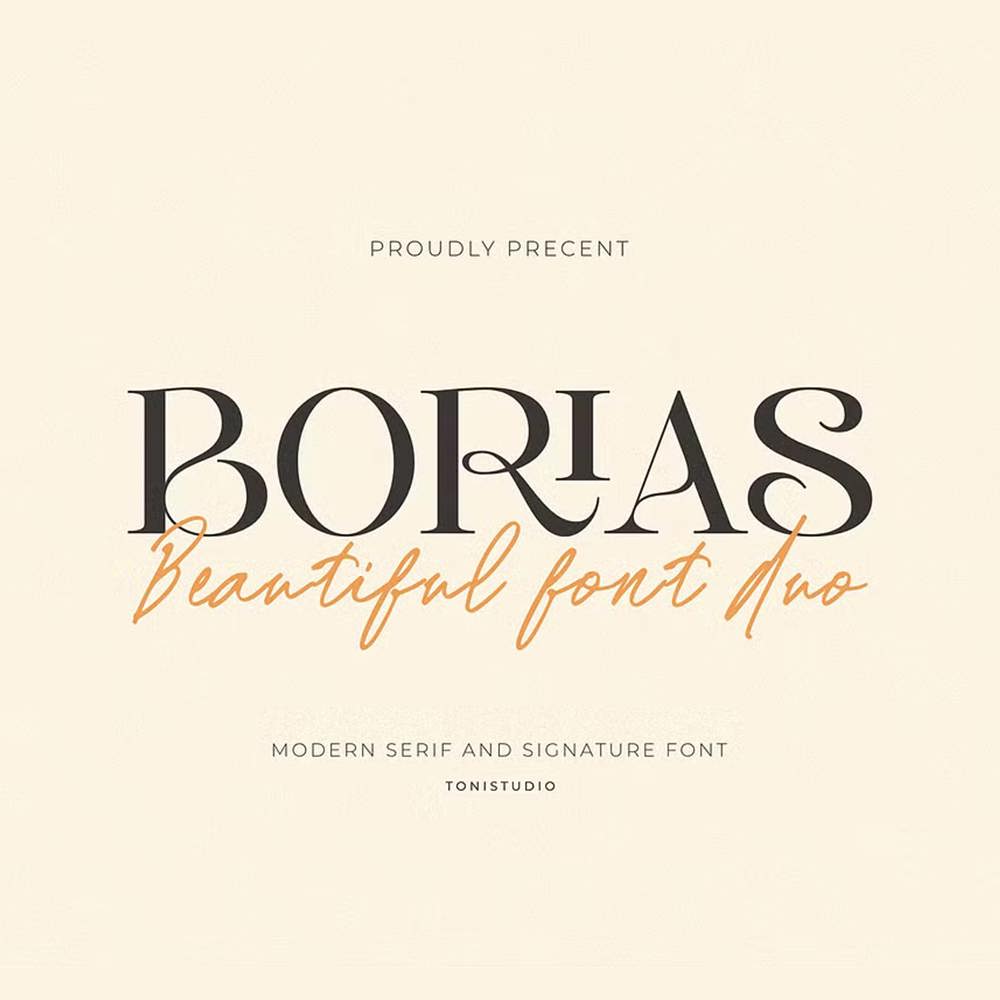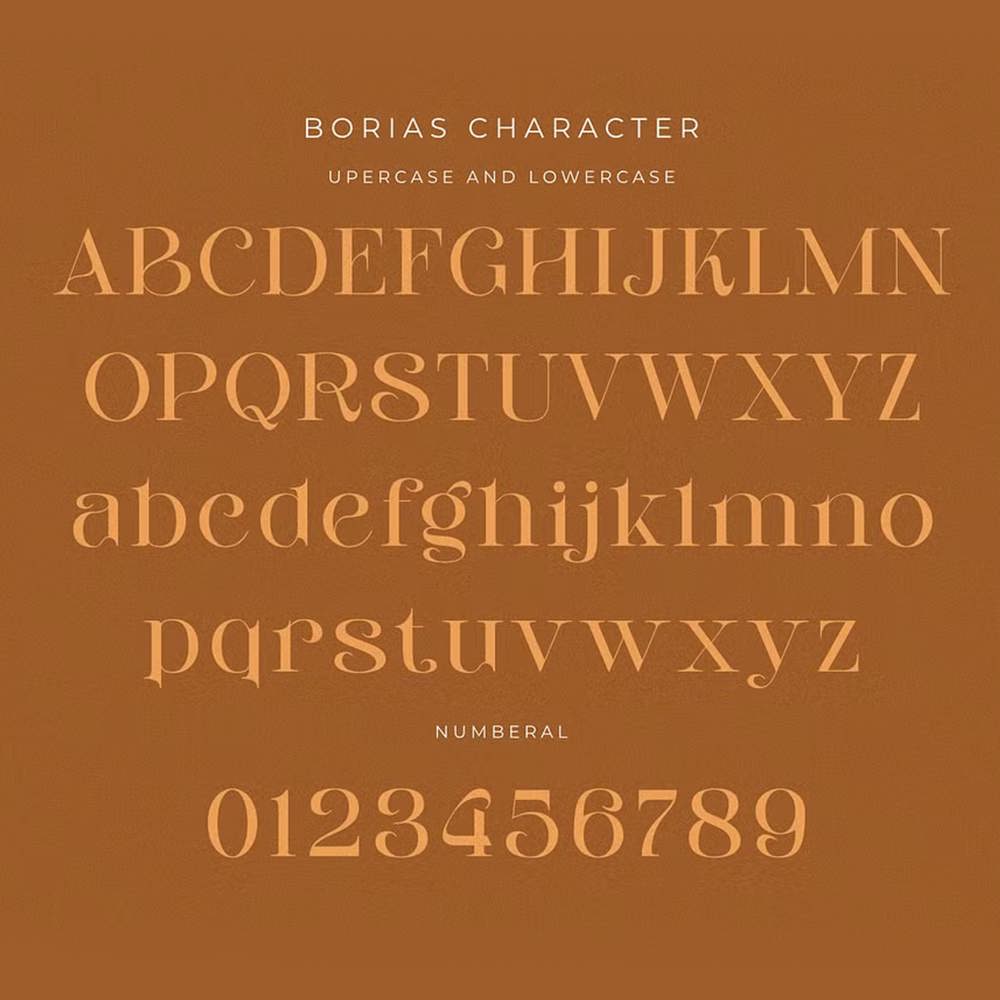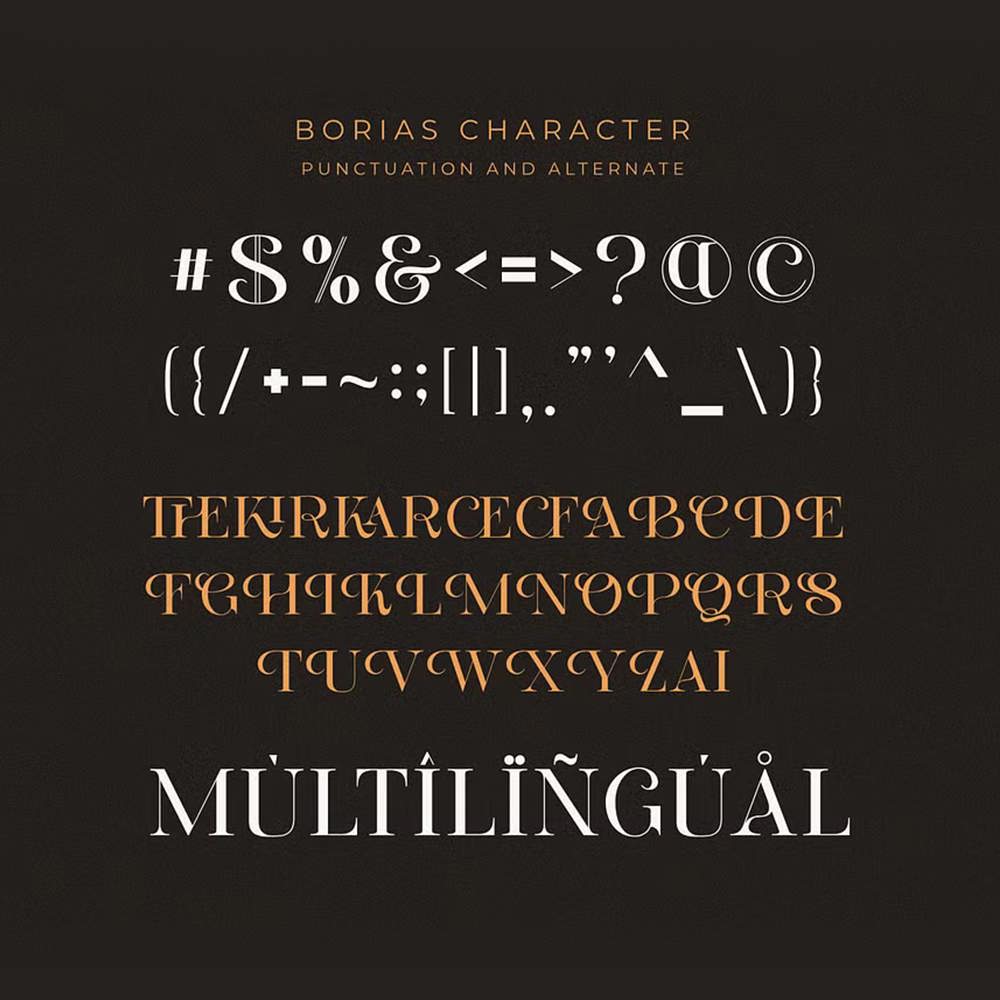
فونت پرمیوم و انگلیسی BORIAS Font ترکیبی بینظیر از یک فونت امضای روان و یک فونت سریف مدرن و زیبا است. Borias که برای ایجاد جلوهای لوکس و باکلاس طراحی شده است، برای انواع پروژههای خلاقانه، از برندسازی گرفته تا طراحی دعوتنامه عروسی، مناسب است. این فونت با ترکیبی هماهنگ از سبکها، زیبایی کلاسیک و مدرن را در یک بسته به ارمغان میآورد. خط دستنویس امضا، نرم، آرام و پر از شخصیت. ظاهری مدرن سریف با جزئیات ظریف، جلوهای حرفهای و زیبا ایجاد میکند. Borias برای برندسازی، لوگو، طراحی دعوتنامه، رسانههای اجتماعی، بستهبندی محصول و موارد دیگر مناسب است.